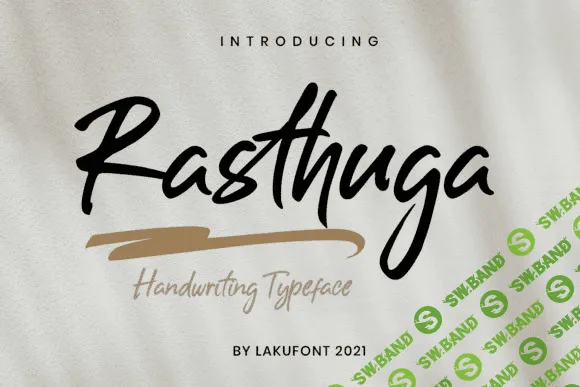
Название: Rasthuga Font
Растуга - стильный и плавный рукописный шрифт.
Этот универсальный скриптовый шрифт имеет широкий спектр применения, начиная от поздравительных открыток и заканчивая детскими поделками, и гарантированно добавит сладкого штриха вашему следующему дизайну.